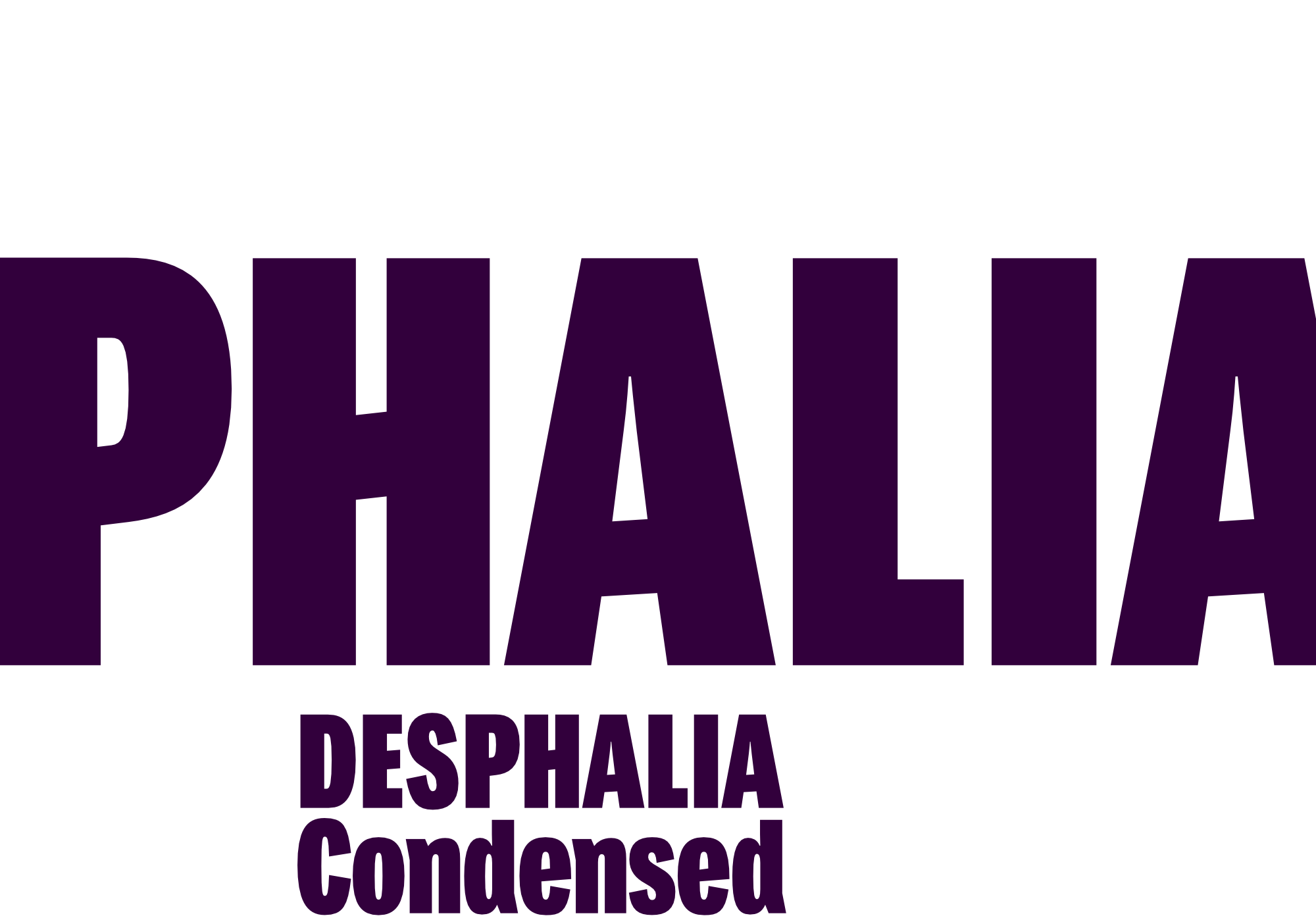
Desphalia appartient au type de polices sans empattement créées au 19ème siècle. Vous pouvez également l’appeler « American Gothic », une police sans empattement dans le style de polices telles que Franklin Gothic, News Gothic et d’autres vieilles connaissances similaires. Surtout, la hauteur d’x caractérise ce style de police, ainsi que les hauteurs identiques des majuscules et des ascendantes.
Je me suis toutefois permis quelques particularités ;-)
D’une part, il y a la barre centrale horizontale légèrement inclinée avec des lettres telles que H, E, F, A et e. Le M a également des côtés légèrement inclinés. Certaines lettres minuscules ont l’allusion d’un sérif : a d m n p u. Ce « pli » sur la tige sert également à mieux distinguer le petit l du grand I – comme le montre clairement le terme « Illinois ».
Conformément à la tradition des écritures américaines, Desphalia ne possède pas de véritable cursive. Les lettres italique ont plutôt les mêmes formes de caractères que la variante verticale normale, mais avec un angle - et elles ne sont donc pas appelées italique mais oblique.
Style Set 01 : Une autre particularité américaine est le I majuscule avec des lignes finales en haut et en bas. Il est inclus dans la Desphalia comme forme de caractère alternative. Un l minuscule alternatif avec le « pli » dans le ascendant est également inclus – tout comme un y avec le « pli » dans le descendeur.
Style Set 02 : Les formes « droites » correspondantes d l m n p u sans courbure sont incluses comme alternatives dans leur propre ensemble de styles.
Petites capitales : Ce sont des lettres majuscules situées à la hauteur visuelle des lettres minuscules - elles offrent une forme d’accentuation très élégante.
Famille de polices : Le Desphalia est disponible en largeurs condensée, normale et étendue, les graisses incluent Thin, Light, Book, Bold, Black.
Lors de l’utilisation de la police variable, tous les niveaux intermédiaires peuvent également être sélectionnés librement.
Les chiffres sont disponibles sous forme de chiffres de table, de chiffres à largeur proportionnelle ou de chiffres médiévaux.